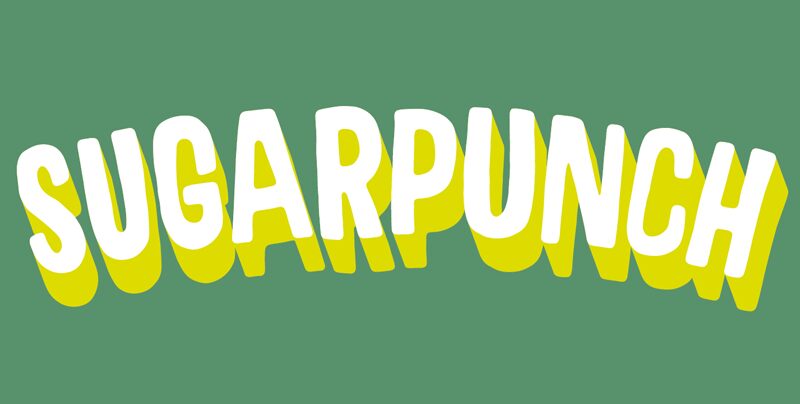
Sugarpunch przypomina smoothie truskawkowo-czekoladowe: jest smaczny, kremowy i po prostu pyszny!
Dzięki zaokrąglonym krawędziom uzyskuje niezwykle miękki wygląd. Idealnie sprawdzi się wszędzie tam, gdzie potrzebny jest ręcznie wykonany styl, zachowując przy tym świetną czytelność nawet w małym rozmiarze. Dostępny w 4 różnych wersjach; każda litera posiada aż 8 zaskakujących wariantów, które zmieniają się automatycznie podczas pisania. Do tego mnóstwo znaków międzynarodowych!